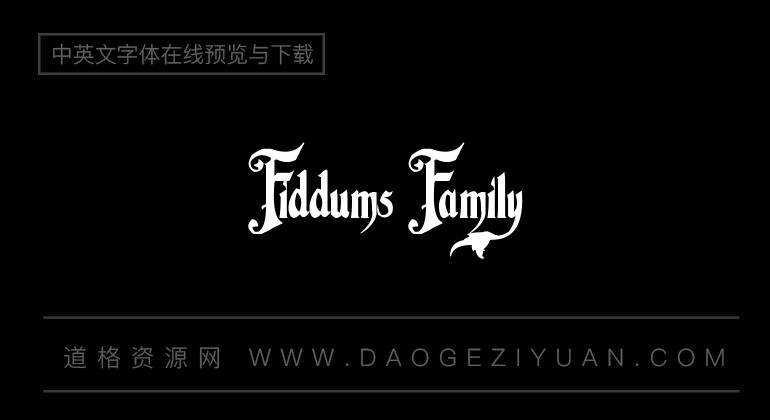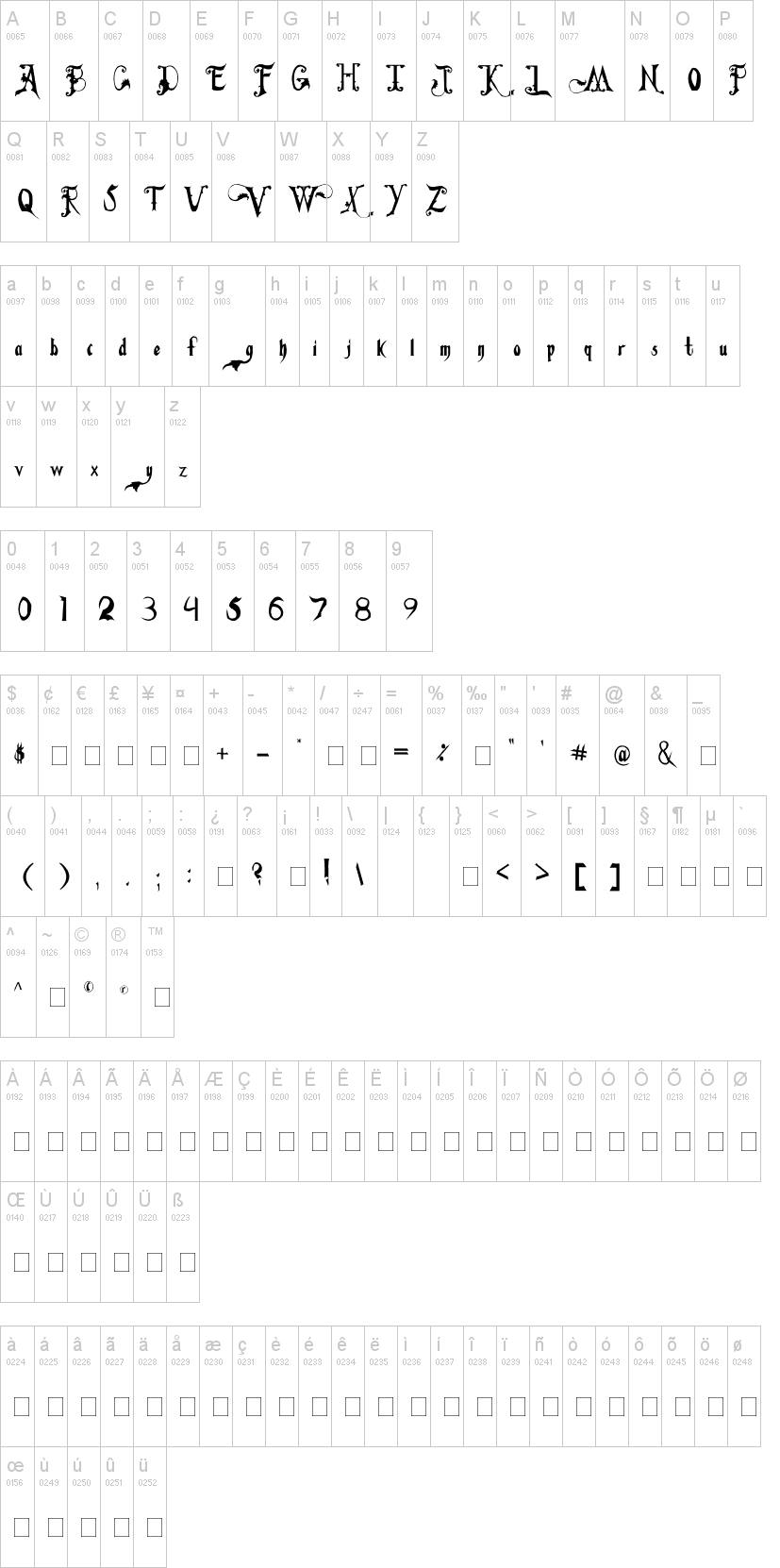
Fiddums Family
Fiddums Family 是一款细节丰富的手写字体,由英国设计师Rob Leuschke设计。它包括7种不同的字体,分别为Fiddums Regular、Fiddums Italic、Fiddums Bold、Fiddums Bold Italic、Fiddums Light、Fiddums Light Italic和Fiddums Black,每种字体都有大量的细节,可以满足不同的设计需求。Fiddums Family 字体细腻,曲线流畅,具有温暖的手写风格,可以用于招牌、标识、商标、海报、T恤等设计项目中。
Fiddums Family是一款非常不错的手写艺术字体,具有很好的视觉感,适合于文化类的宣传设计、商业类品牌的广告和产品包装设计以及个性化文字排版等较多场景。